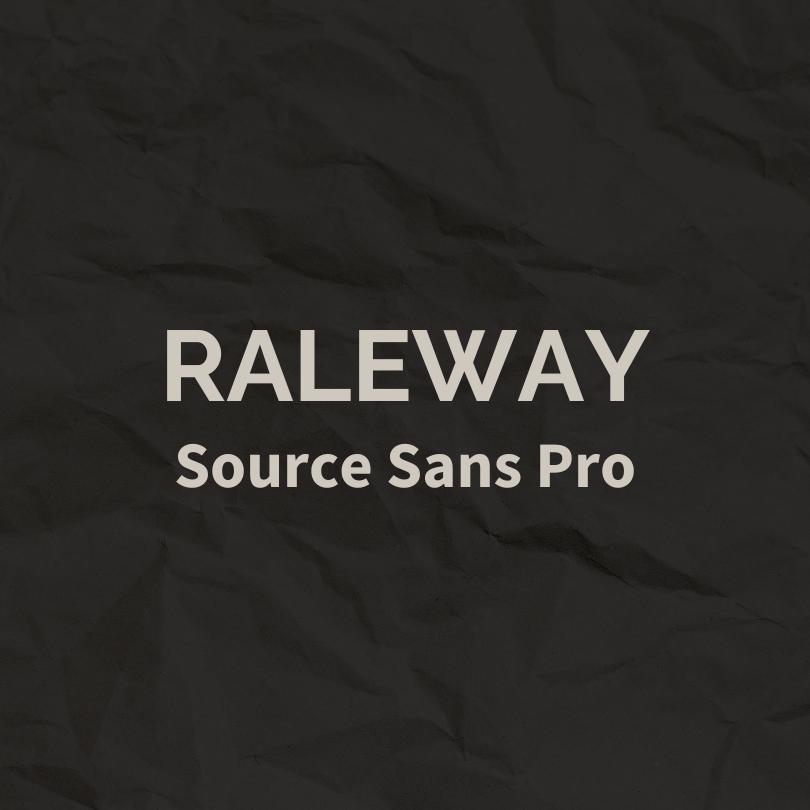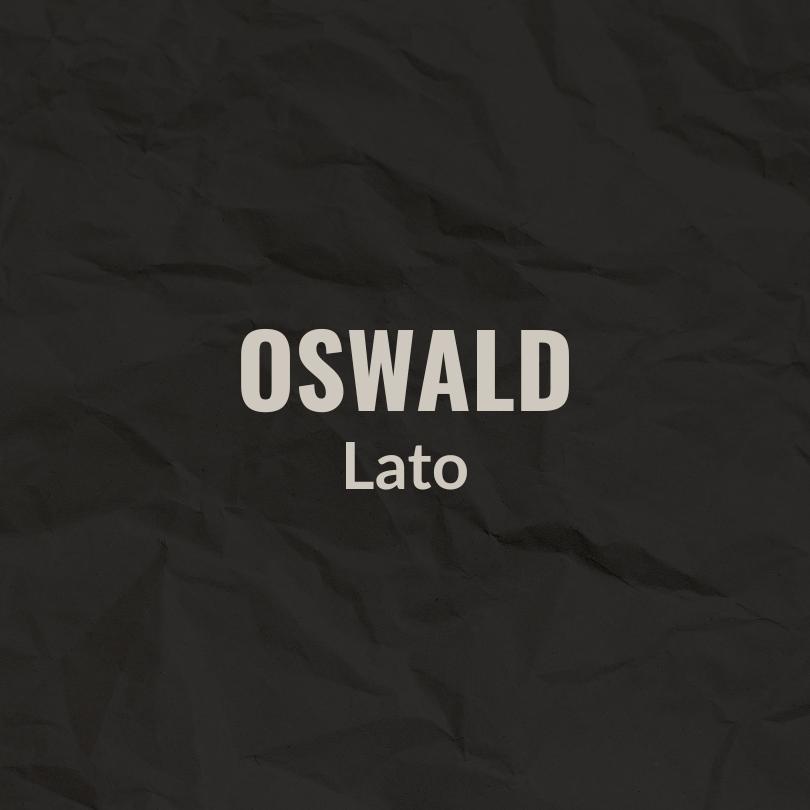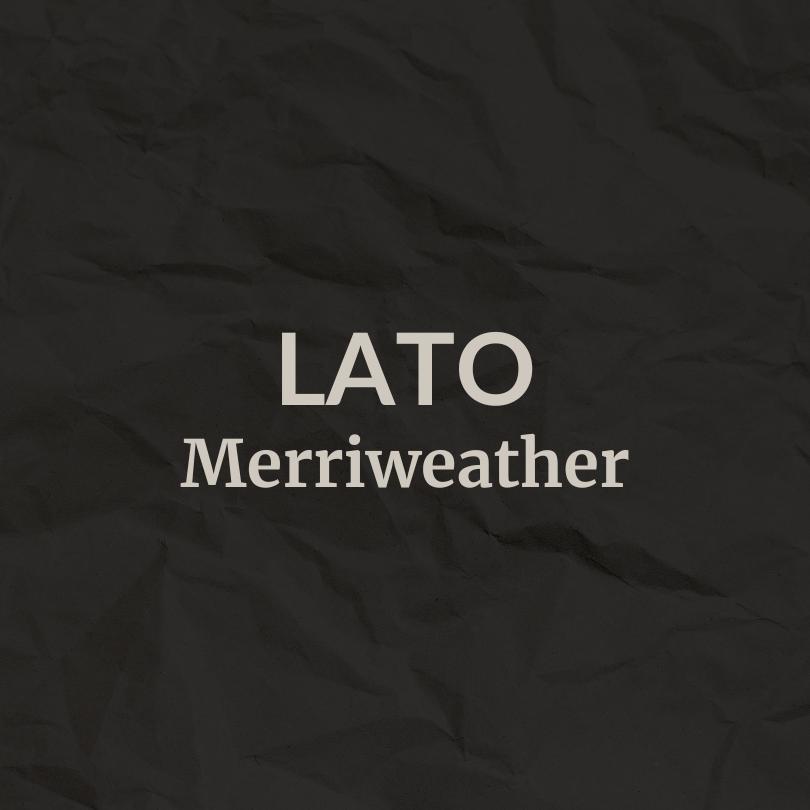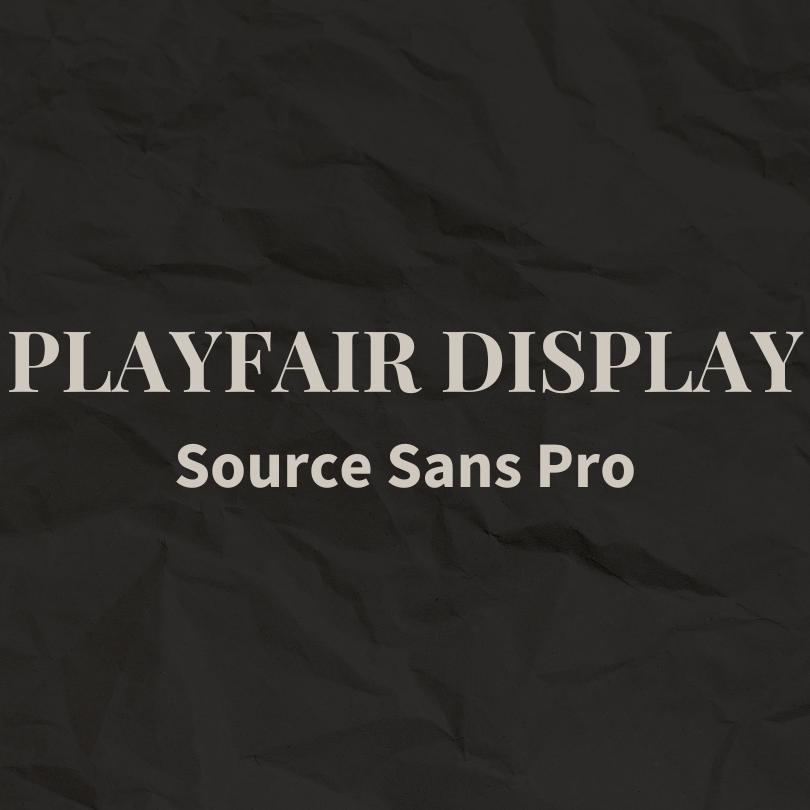
5 Kombinasi Font Canva untuk Konten Formal, Gak Bikin Kaku
Di era digital, konten di media sosial kini adalah makanan sehari-hari bagi masyarakat. Apapun tujuanmu menggunakan media sosial, baik untuk berbagi informasi, promosi produk dan jasa, ataupun personal branding semua itu akan dapat tercapai jika kamu membuat dan mengunggah konten. Salah satu konten yang kerap ditemui adalah bernuansa formal.
Tak hanya isi konten, layout desain dan juga pemilihan font yang tepat adalah unsur penting agar pesan yang disampaikan dapat diterima dengan baik oleh audiens. Kalau kalian sedang mencari kombinasi font Canva untuk konten formal, berikut ini rekomendasi yang bisa kamu pakai, ya!
1. Montserrat dan Roboto Slab
Kombinasi Montserrat untuk judul dan Roboto Slab untuk teks menawarkan sentuhan modern dan bersih yang ideal untuk konten formalmu. Montserrat adalah font sans-serif yang mudah dibaca dan bersih, memberikan kesan kekinian dan resmi pada judul. Sementara itu, Roboto Slab memberikan elemen serif yang memberikan karakter dan keunikan pada teks, cocok untuk menegaskan elemen formalitas pada konten.
Dengan Montserrat, hook kontenmu akan memiliki tampilan yang menonjol, menarik perhatian tanpa kehilangan kejelasan. Di sisi lain, Roboto Slab memberikan keleluasaan dalam mengekspresikan ide dan informasi secara rinci melalui teks panjang tanpa kehilangan fokus pembaca.
2. Playfair Display dan Source Sans Pro
Jika kamu menginginkan kesan formal, tapi elegan, kombinasi Playfair Display untuk judul dan Source Sans Pro untuk teks bisa menjadi pilihan yang sempurna. Playfair Display, dengan desain serif yang elegan, memberikan nuansa formal dan mewah pada judul kontenmu. Sementara itu, Source Sans Pro adalah font sans-serif yang bersih dan serbaguna, ideal untuk teks yang mudah dibaca dan tetap modern.
Dengan kombinasi ini, kontenmu akan terlihat profesional dan tetap relevan dengan estetika modern. Playfair Display memberikan elemen klasik yang bisa menonjolkan unsur formalitas, sementara Source Sans Pro memastikan konten tetap bersahabat dan mudah dipahami.
3. Raleway dan Source Sans Pro
Kombinasi Raleway untuk judul dan Source Sans Pro untuk teks memberikan sentuhan modern dan inovatif pada desain kontenmu. Raleway adalah font sans-serif dengan desain futuristik yang menciptakan tampilan modern dan inovatif pada judul. Sementara itu, Source Sans Pro memberikan kebersihan dan keterbacaan pada teks, membuatnya jadi pilihan yang ideal untuk konten formal.
Raleway dapat memberikan kontenmu sentuhan kekinian dan inovatif yang dapat menarik perhatian target audiens. Di sisi lain, Source Sans Pro memastikan bahwa informasi yang disajikan dalam teks tetap dapat diakses dengan mudah dan profesional.
4. Lato dan Merriweather
Jika kamu mencari kombinasi yang menciptakan kesan formal namun tetap santai, pilihlah Lato untuk judul dan Merriweather untuk teks. Lato adalah font sans-serif yang bersahaja dan serbaguna, ideal untuk judul yang ingin terlihat resmi, tapi tetap modern. Merriweather, sebagai font serif, memberikan kesan formal dan mudah dibaca pada teks, cocok untuk menciptakan keseimbangan antara formalitas dan kehangatan.
Dengan Lato, judul kontemu akan memiliki tampilan yang bersahabat namun tetap elegan. Di sisi lain, Merriweather pada teks memastikan bahwa pesan yang disampaikan tetap terlihat profesional dan mudah dicerna oleh pembaca.
5. Oswald dan Lato
Ilustrasi font canva (dok. Canva)
Oswald untuk judul dan Lato untuk teks adalah kombinasi yang menyajikan kesan kuat dan bersahaja. Oswald, sebagai font sans-serif yang kuat dan berat, menciptakan tampilan judul yang menarik perhatian. Sementara itu, Lato adalah font sans-serif yang bersahaja dan serbaguna, ideal untuk teks panjang dan memberikan tampilan yang bersahabat.
Kombinasi ini cocok untuk konten yang memerlukan kesan tegas dan fokus pada judul, sementara teksnya tetap dapat diakses dan dipahami dengan mudah. Lato memberikan keseimbangan yang baik antara kesan profesional dan santai.
Kombinasi font Canva untuk konten formal tadi dijamin meningkatkan daya tarik visual dari kontenmu. Canva menyediakan berbagai opsi font dan fleksibilitas untuk eksplorasi kreatif. Jadi, temukan kombinasi yang paling sesuai dengan brand-mu dan sampaikan pesanmu dengan tampilan yang apik dan menarik.